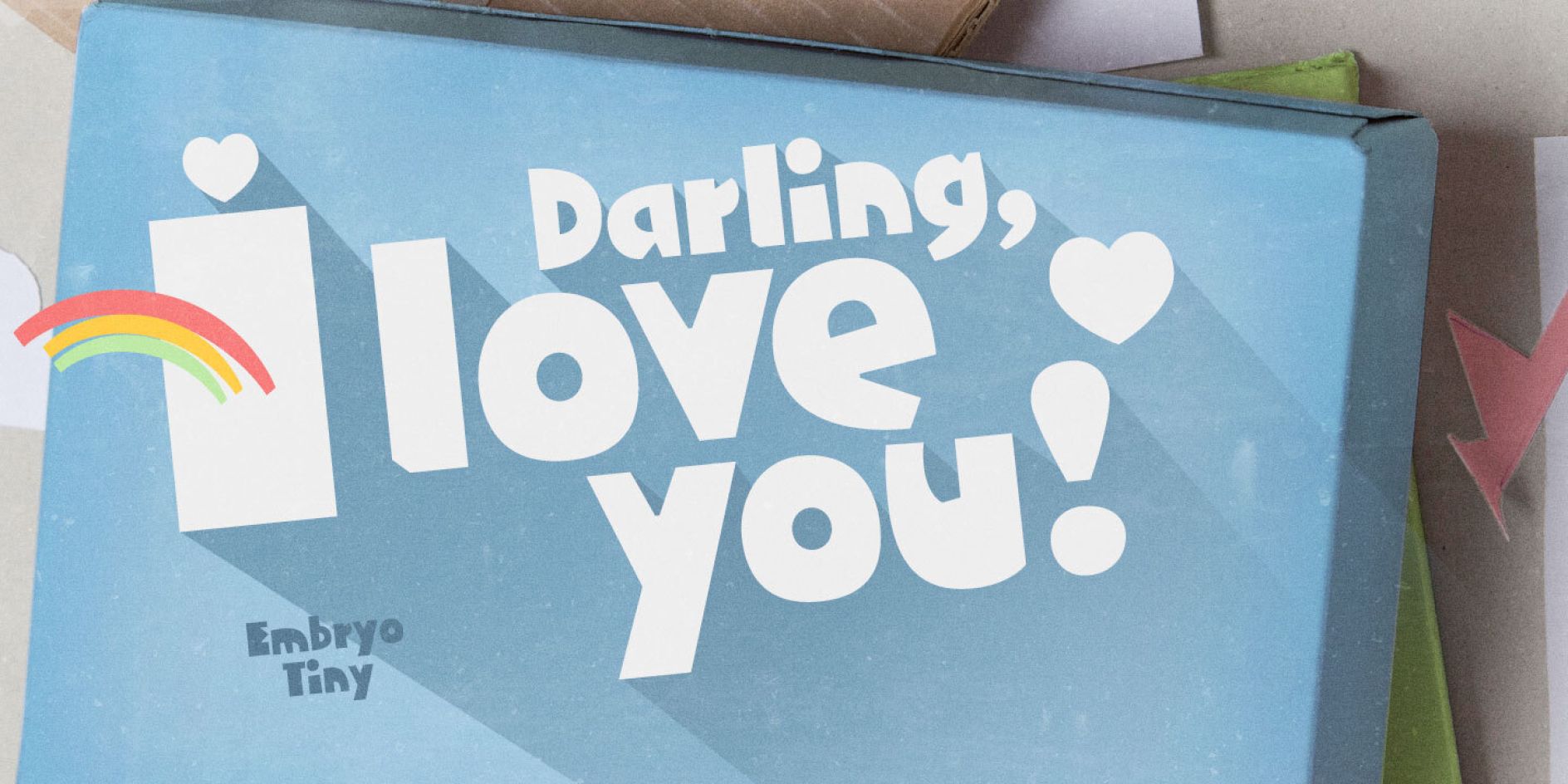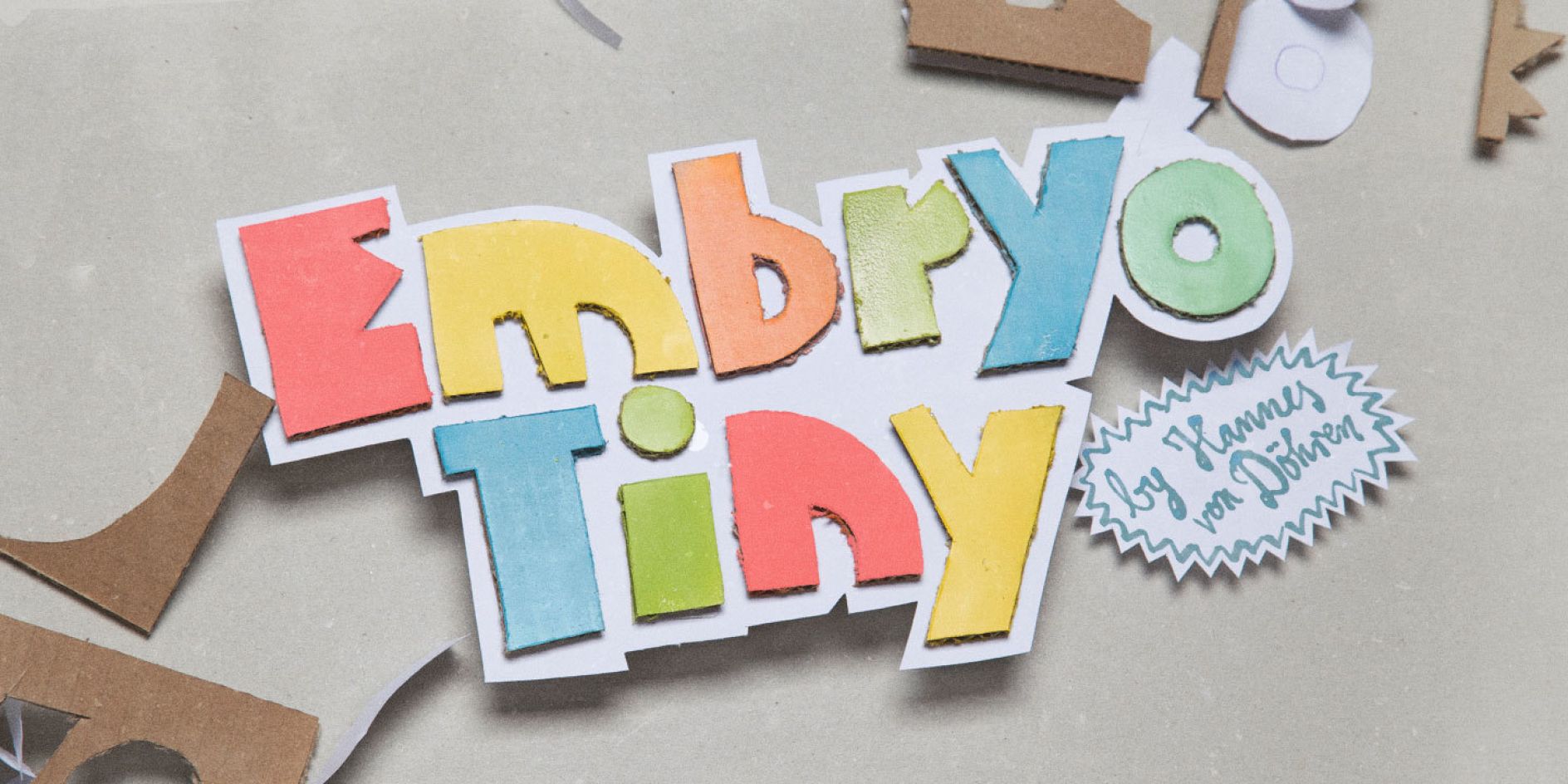
Danh sách này không chỉ mang đến cho bạn cái nhìn tổng quan về những kiểu chữ thiết kế phá cách, mà còn giới thiệu những xu hướng tiên phong đang định hình tương lai của nghệ thuật typography. Nếu bạn đang tìm kiếm nguồn cảm hứng để nâng tầm thương hiệu, tạo dấu ấn cho sản phẩm truyền thông, hay xây dựng giao diện kỹ thuật số đột phá, bài viết này chính là cánh cửa dẫn lối vào thế giới typography hiện đại, đầy sáng tạo của năm 2025.
Sau khi khám phá hai phần đầu tiên với vô số kiểu chữ sáng tạo và độc đáo, chúng ta đã đi qua một chặng đường đầy cảm hứng. Phần 3, phần cuối cùng của bài viết, sẽ đưa bạn đến những lựa chọn phông chữ đặc sắc nhất, nơi sự sáng tạo và tính ứng dụng đạt đến đỉnh cao.
Ở đây, bạn sẽ tìm thấy những kiểu chữ không chỉ mang phong cách tiên phong mà còn gói trọn giá trị thẩm mỹ vượt thời gian, từ những thiết kế táo bạo cho thương hiệu, các dự án kỹ thuật số hiện đại, đến những kiểu chữ tinh tế dành cho biên tập và bao bì cao cấp. Mỗi kiểu chữ trong phần này đều được chọn lọc kỹ lưỡng để mang lại sự khác biệt, giúp bạn truyền tải thông điệp một cách mạnh mẽ và hiệu quả nhất.
Hãy sẵn sàng bước vào chặng cuối của hành trình này, nơi bạn sẽ gặp những kiểu chữ hứa hẹn sẽ định hình không chỉ xu hướng năm 2025 mà còn là tương lai của typography. Chắc chắn, bạn sẽ tìm thấy những cái tên phù hợp để nâng tầm mọi ý tưởng thiết kế của mình đấy!
32. Font chữ: SWORDFISH (CAST Studies)
Swordfish là kiểu chữ sans serif hình học sử dụng toàn bộ chữ in hoa, được thiết kế để phục vụ tối ưu cho các mục đích display, xây dựng thương hiệu, và tiêu đề nổi bật. Kiểu chữ này lấy cảm hứng từ những thiết kế tiên phong của thập niên 1920 và 1930, khi phong cách hiện đại bắt đầu định hình, kết hợp với sự phóng khoáng và cá tính của bìa đĩa nhạc jazz từ thập niên 1940 và 1950. Sự hòa quyện giữa tinh thần lịch sử và thiết kế táo bạo hiện đại đã tạo nên Swordfish mang sức hút thị giác mạnh mẽ.
Với các đường nét đậm, hình học rõ ràng, và phong cách kịch tính, Swordfish không chỉ gợi lên cảm giác hoài cổ mà còn mang tính thời thượng, lý tưởng cho các dự án đòi hỏi sự ấn tượng và thu hút. Từ poster, tiêu đề lớn, đến thiết kế thương hiệu cá tính, Swordfish mang lại sự tự tin và mạnh mẽ trong mọi ứng dụng, là lựa chọn hoàn hảo cho những dự án muốn ghi dấu ấn mạnh mẽ trong tâm trí người xem.
33. Font chữ: Mattone (Collletttivo)
Mattone là kiểu chữ display sans serif vô cùng độc đáo và sáng tạo, nổi bật với hình dáng chữ đặc trưng, tỷ lệ chiều rộng thoáng đãng, và các đường cong đầy táo bạo. Kiểu chữ này không chỉ thu hút sự chú ý mà còn mang lại cảm giác hiện đại, mạnh mẽ, lý tưởng cho các thiết kế đòi hỏi sự nổi bật và khác biệt.
Ban đầu, Mattone được ra mắt vào năm 2017 với mục đích phục vụ cho các thiết kế display, tập trung vào các ứng dụng tiêu đề lớn hoặc poster. Tuy nhiên, vào năm 2021, kiểu chữ này đã được tái thiết kế hoàn toàn từ đầu, không chỉ cải tiến về mặt kỹ thuật mà còn mở rộng khả năng ứng dụng. Mattone giờ đây có thể được sử dụng cho các đoạn văn bản dài ở kích thước nhỏ, đồng thời hỗ trợ đa dạng ngôn ngữ, làm tăng tính linh hoạt và phù hợp với nhiều loại dự án. Với sự kết hợp giữa thẩm mỹ sáng tạo và chức năng vượt trội, Mattone là lựa chọn hoàn hảo cho những nhà thiết kế muốn truyền tải sự mạnh mẽ và khác biệt qua từng chi tiết.
34. Font chữ: Embryo (Hannes von Döhren)
Embryo là kiểu chữ display sở hữu thiết kế mềm mại, các đường nét bo tròn mang đến phong cách vui tươi, gần gũi và tràn đầy sức sống. Kiểu chữ này được xây dựng dựa trên một ý tưởng độc đáo: Tạo ra một kiểu chữ như đang trong quá trình phát triển, chưa hoàn toàn hoàn chỉnh. Như nhà thiết kế Hannes von Döhren chia sẻ: “Các chữ cái đã có thể nhận diện được, nhưng chúng vẫn chưa thực sự hoàn thiện.” Chính sự chưa hoàn chỉnh này lại là yếu tố tạo nên nét duyên dáng đặc biệt của Embryo.
Kết quả là một kiểu chữ siêu ngọt ngào, với đường nét đậm nét, nổi bật nhưng vẫn đảm bảo dễ đọc. Embryo không chỉ mang lại sự tươi mới mà còn gợi lên cảm giác tự nhiên, rất phù hợp cho các dự án thiết kế muốn truyền tải sự vui vẻ, thân thiện và đầy sáng tạo. Với sự kết hợp giữa tính thẩm mỹ độc đáo và khả năng ứng dụng linh hoạt, Embryo trở thành lựa chọn lý tưởng cho các thiết kế thương hiệu, tiêu đề nổi bật hay bất kỳ dự án nào cần một phong cách trẻ trung và cuốn hút.
35. Font chữ: Poppins (Indian Type Foundry, Jonny Pinhorn, Ninad Kale)
Poppins là kiểu chữ sans serif hình học hiện đại, được thiết kế để đáp ứng tối ưu nhu cầu của các dự án display và thiết kế web. Với khả năng hỗ trợ cả hai hệ chữ Devanagari và Latin, Poppins thể hiện sự linh hoạt vượt trội, phù hợp cho nhiều đối tượng và ngữ cảnh sử dụng. Điểm chung nổi bật của cả hai hệ chữ này là sự tuân thủ chặt chẽ các nguyên tắc hình học, đặc biệt nhấn mạnh vào việc sử dụng các hình tròn và các đường nét gần như đồng nhất, mang lại vẻ đẹp cân đối và tối giản.